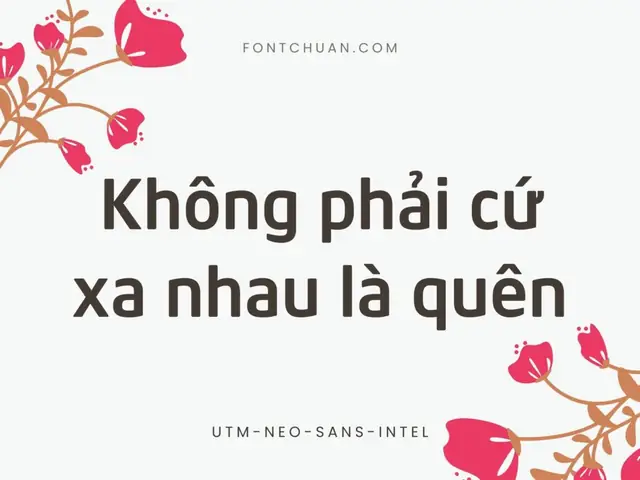
Font UTM Neo Sans Intel là một trong những bộ font tiếng Việt phổ biến và được ưa chuộng hàng đầu hiện nay. Với thiết kế hiện đại, thanh lịch và khả năng hiển thị xuất sắc, bộ font này đã trở thành lựa chọn hàng đầu của các nhà thiết kế, dân văn phòng và sinh viên trong các công việc liên quan đến soạn thảo, thiết kế đồ họa, trình chiếu và in ấn. Font UTM Neo Sans Intel sở hữu nét chữ rõ ràng, dễ đọc, đặc biệt phù hợp với các văn bản hành chính, tài liệu học thuật và các ấn phẩm chuyên nghiệp.
Font UTM Neo Sans Intel là một trong những font chữ tiếng Việt phổ biến nhất hiện nay, được phát triển bởi nhóm UTM (University of Technology and Management) tại TP. Hồ Chí Minh. Font này là phiên bản làm lại của phông chữ nổi tiếng Neo Sans Intel, được tối ưu hóa đặc biệt cho việc hiển thị tiếng Việt với đầy đủ bộ ký tự Unicode, bao gồm cả các dấu tiếng Việt phổ biến như huyền, sắc, hỏi, ngã, nặng. Với thiết kế hiện đại, thanh lịch và dễ đọc, Font UTM Neo Sans Intel phù hợp cho nhiều mục đích sử dụng khác nhau, từ soạn thảo văn bản, thiết kế đồ họa đến in ấn tài liệu.